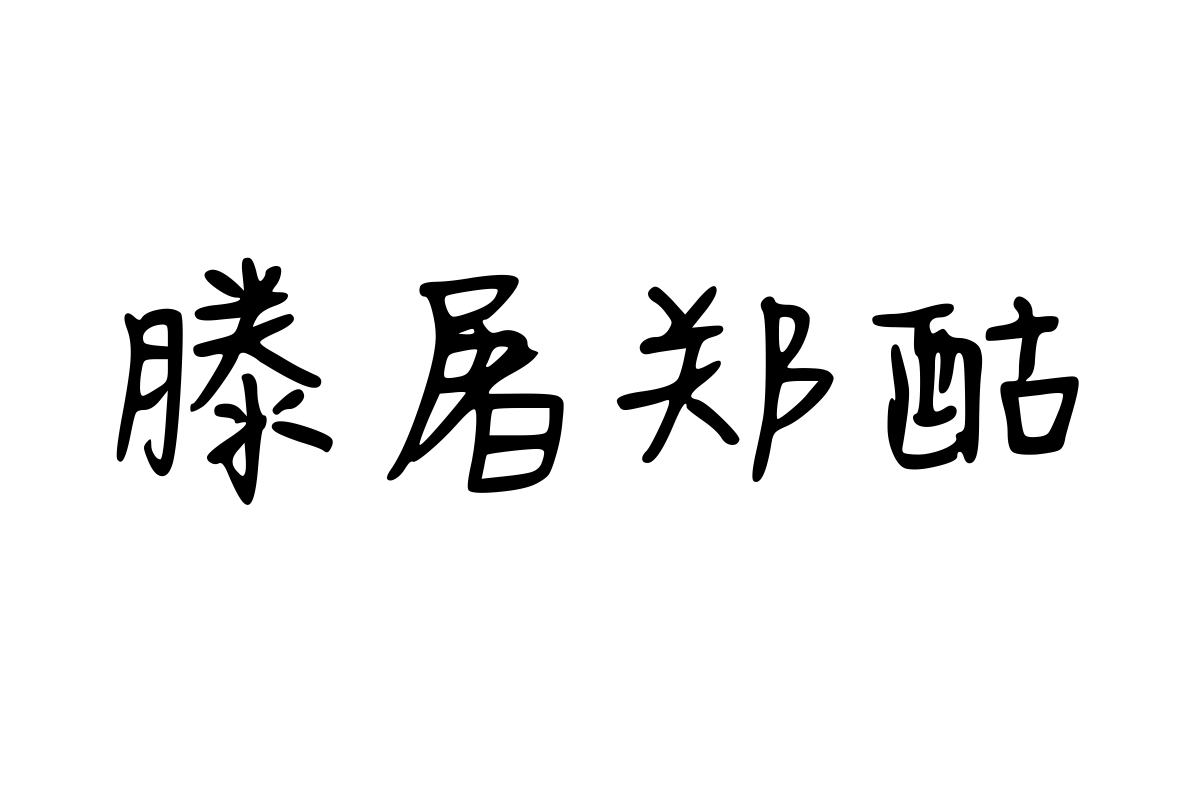
思雨字体-楼外青山体是一种具有独特风格的中文字体,其特点是字形圆润饱满,线条流畅自然。这种字体适合用于各种需要展现柔和、优雅氛围的场合,如广告设计、书籍装帧、网页设计等。
思雨字体-楼外青山体的笔画粗细适中,既不会过于纤细导致难以辨认,也不会过于粗壮影响整体美感。这种字体的结构紧凑,但不失灵动,使得整体视觉效果既稳重又富有变化。
此外,思雨字体-楼外青山体还具有一定的艺术感,能够给人带来一种宁静、舒适的视觉体验。无论是在正式的商业环境中还是在轻松的休闲场合,这种字体都能够很好地适应并展现出其独特的魅力。